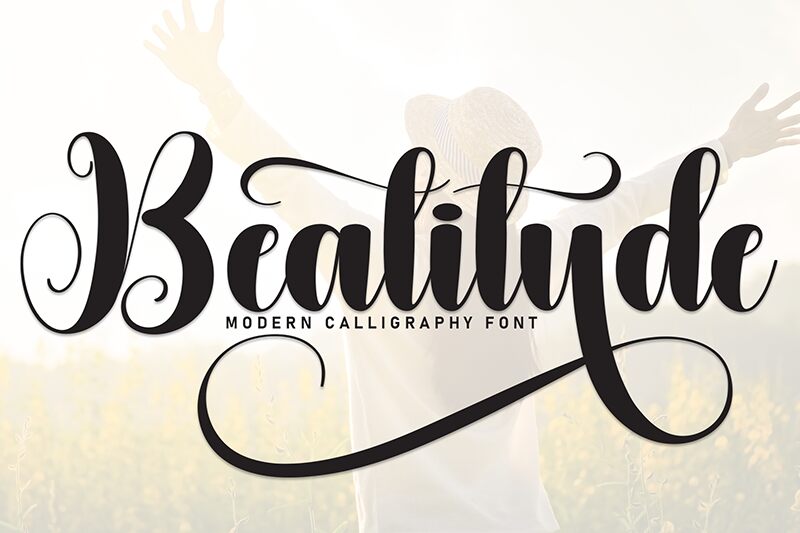
Beatitude
Beatitude è un font calligrafico gratuito ispirato al segno del pennello, con un fascino elegante e senza tempo. Le lettere si distinguono per il marcato contrasto tra tratti spessi e sottili, per i lunghi tratti d’ingresso sinuosi e per le giunzioni arrotondate: un design che trasmette il calore di una scritta manuale, superando di gran lunga le forme standard dei font script.
È perfetto per il packaging di prodotti beauty, loghi di boutique, partecipazioni nuziali, testate di riviste o per il brand di un caffè, dove serve un tocco di classe che non risulti rigido. Usalo per titoli brevi, iniziali o monogrammi: i suoi riccioli ampi e i tratti fluidi come nastri hanno bisogno di spazio per esprimere tutta la loro bellezza.